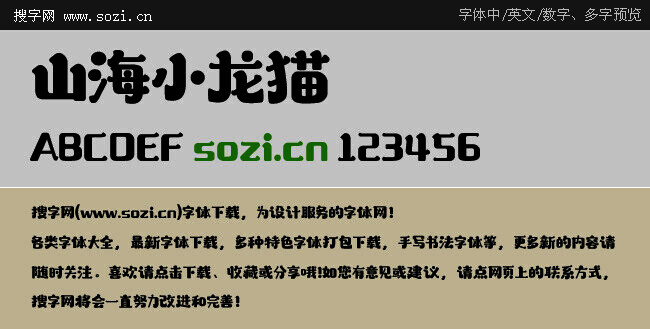
山海小龍貓
搜字網(wǎng)提供一款山海小龍貓中文藝術(shù)字體下載,山海小龍貓是一款卡通風(fēng)字體,包含簡體漢字6763個。字體童趣可愛,結(jié)構(gòu)多變靈動,字形活潑清新,造型生動有趣,具有靈活的適用性,天真俏皮又不失時尚感。適合兒童包裝設(shè)計、卡通海報設(shè)計、廣告設(shè)計等應(yīng)用。